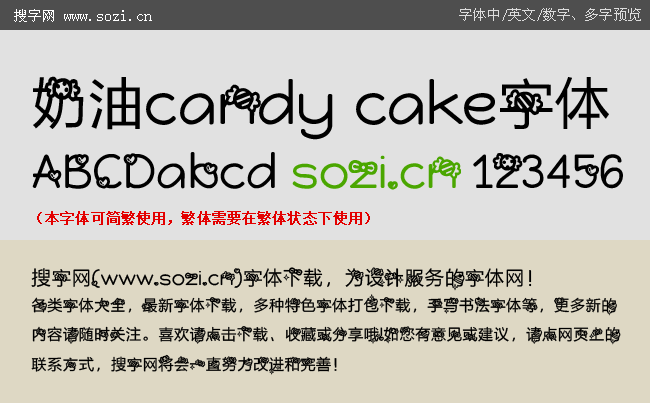
奶油candy cake字體
搜字網(wǎng)給大家提供一款奶油candy cake字體手機(jī)中文字體下載。這款手機(jī)字體是以黑體字體為原形,在字體間嵌入了卡通糖果圖案。具有黑體端正易認(rèn)的風(fēng)格,又很有趣味性,特別適合喜歡手機(jī)字體個(gè)性一些的朋友在手機(jī)上安裝使用。